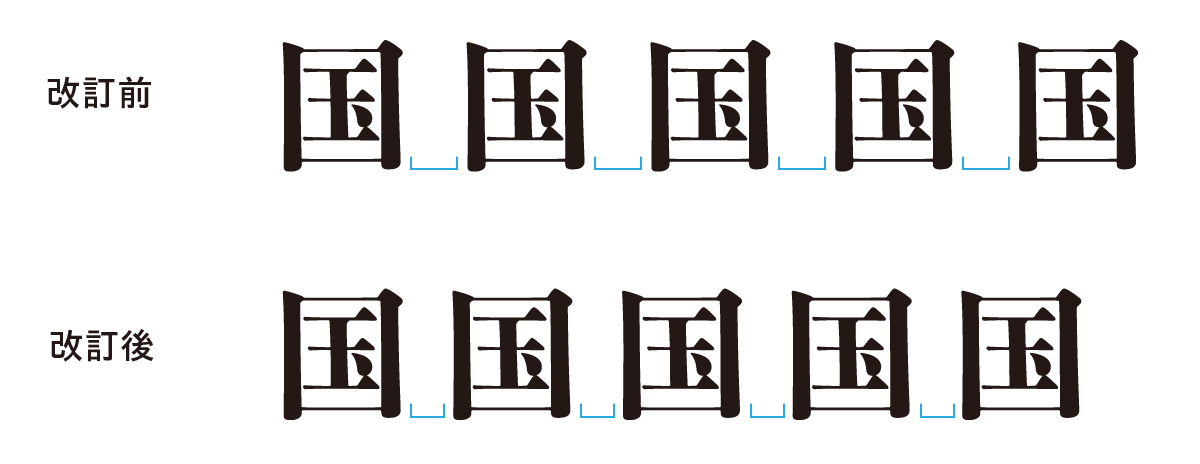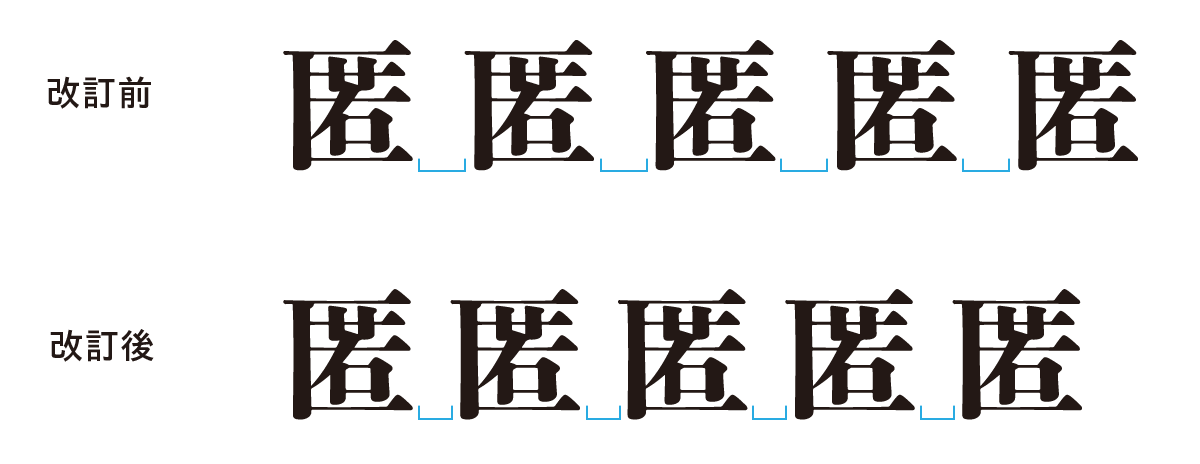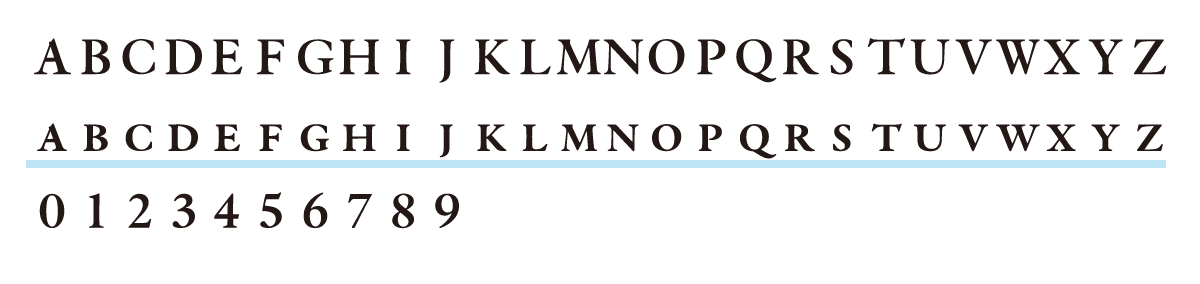
游築見出し明朝体は、2003年にリリースされたフォントです。
想定するユーザーや使用環境からリリース時には従属欧文(和文書体の中に含まれる欧文)を搭載していませんでしたが、 ユーザーの利便性を高めることを目的として、欧文を搭載しました。
游築見出し明朝体 Altは、OpenTypeフォントの字形切り替え機能が利用できないアプリケーションや出力環境で游築見出し明朝体の異体字が使えるように、同じユニコードに異体字グリフを収容したフォントです。游築見出し明朝体の従属欧文搭載にあわせて、従属欧文の代替字形を搭載しました。
アップデート・改訂内容
主に以下の改訂を行いました。
游築見出し明朝体
・プロポーショナル幅のスペース(U+0020)の文字幅を変更
・プロポーショナル幅の英数字(正体・イタリック体)を追加
正体
イタリック体
・上付き数字/下付きの数字(正体・イタリック体)を追加
正体
イタリック体
・全角の英数字追加
游築見出し明朝体 Alt
・プロポーショナル幅のスペース(U+0020)の文字幅を変更
・スモールキャップスのグリフ(正体・イタリック体)を追加
※大文字は游築見出し明朝体と同様のデザイン
正体
イタリック体
・オールドスタイル数字(正体・イタリック体)を追加
・上付き数字/下付き数字(正体・イタリック体)を追加
※游築見出し明朝体と同様のデザイン
正体
イタリック体
・全角の英数字追加
※数字・大文字は游築見出し明朝体と同様のデザイン
※小文字はスモールキャップスのデザイン